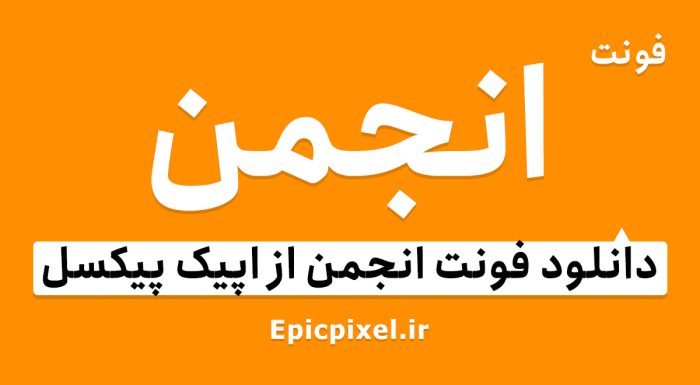
فونت انجمن، انتخابی ایده آل برای طراحان گرافیک و وب سایت ها، با ویژگی های منحصربه فرد خود، تجربه ای متفاوت از تایپوگرافی فارسی را ارائه می دهد. این فونت از استانداردهای بالایی در طراحی برخوردار است و همین امر، تضمینی برای کیفیت و زیبایی آن محسوب می شود.
یکی از ویژگی های برجسته فونت انجمن، خوانایی بالای آن است؛ طراحی دقیق حروف و فاصله گذاری مناسب بین آن ها، خواندن متن را برای مخاطب آسان و لذت بخش می کند. این ویژگی به ویژه در طراحی وب سایت ها و رابط های کاربری که خوانایی متن اهمیت زیادی دارد، بسیار حائز اهمیت است. همچنین، فونت انجمن از تنوع بالایی در وزن ها و سبک ها برخوردار است و این امکان را به طراحان می دهد تا در پروژه های مختلف، از سبک های متنوع این فونت بهره ببرند و به طرح خود، جلوه ای خاص و حرفه ای ببخشند.
علاوه بر این، فونت انجمن از زبان های فارسی، عربی، کردی، اردو و انگلیسی پشتیبانی می کند که این ویژگی، آن را به گزینه ای مناسب برای پروژه های چندزبانه تبدیل کرده است. پشتیبانی از اعداد فارسی و طراحی هماهنگ حروف انگلیسی و فارسی، از دیگر ویژگی های این فونت ارزشمند است. با دانلود فونت انجمن، شما به مجموعه ای کامل از فونت های باکیفیت دسترسی پیدا می کنید که می تواند در پروژه های مختلف، از طراحی لوگو و بنر گرفته تا طراحی وب سایت و اپلیکیشن، مورد استفاده قرار گیرد و به آن ها، هویتی بصری منحصربه فرد ببخشد.
| ⭐ توضیحات | مجموعه ای کامل از فونت های انجمن و نسخه شبیه سازی شده اپیک انجمن مکس و معمولیفونت عربوتو عربی فارسیدانلودفونت اپیک انجمن با پشتیبانی از حروف فارسی ، انگلیسی / لاتین ، اعداد فارسی Fu Num شامل نسخه Variable . وزن های Condensed ، ایتالیک و نسخه وب . داخل مجموعه نسخه ی قدیمی تر هم موجوده 4 مدل مختلف نقطه انجمن کاملا شبیه سازی شده |